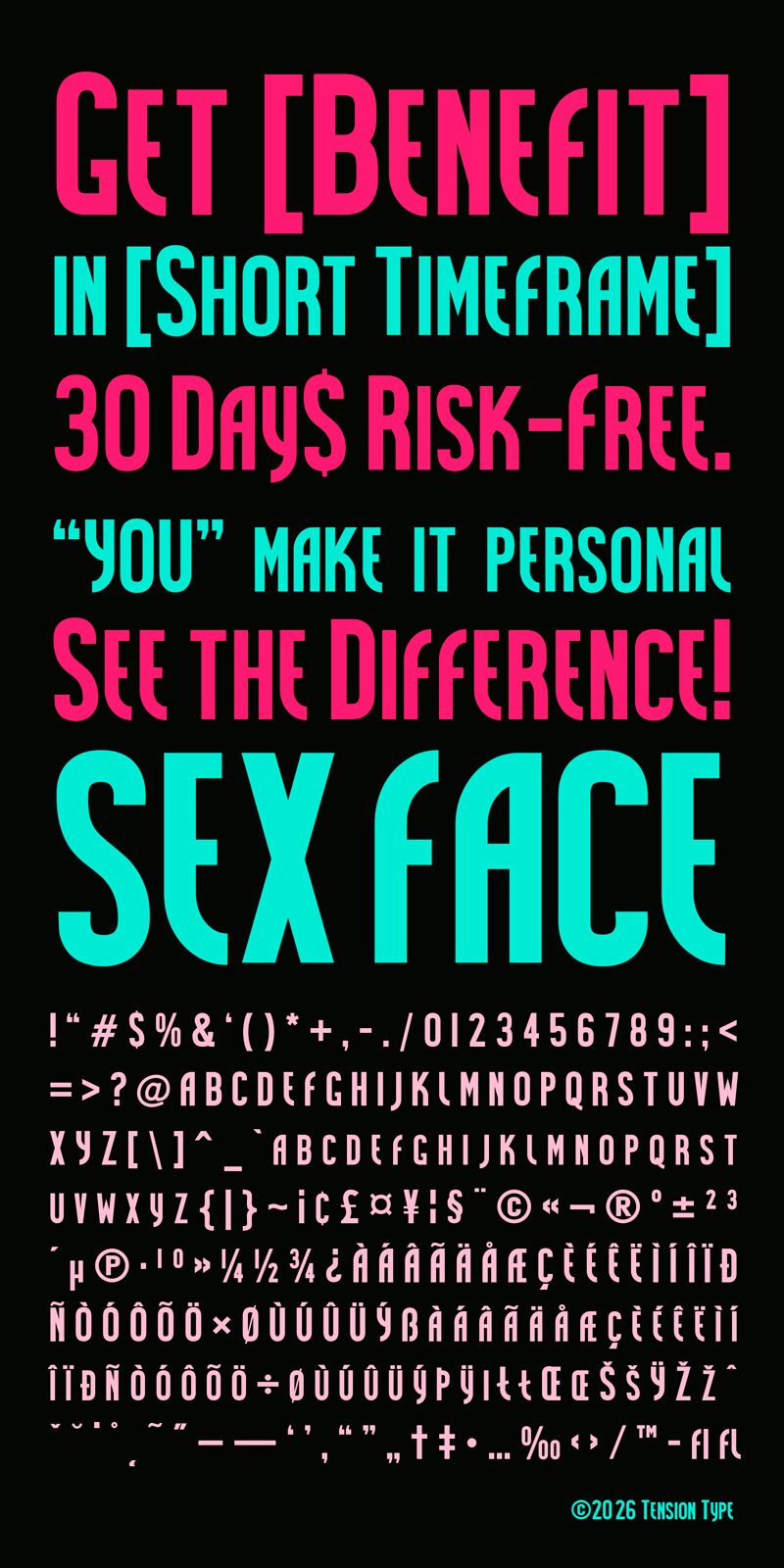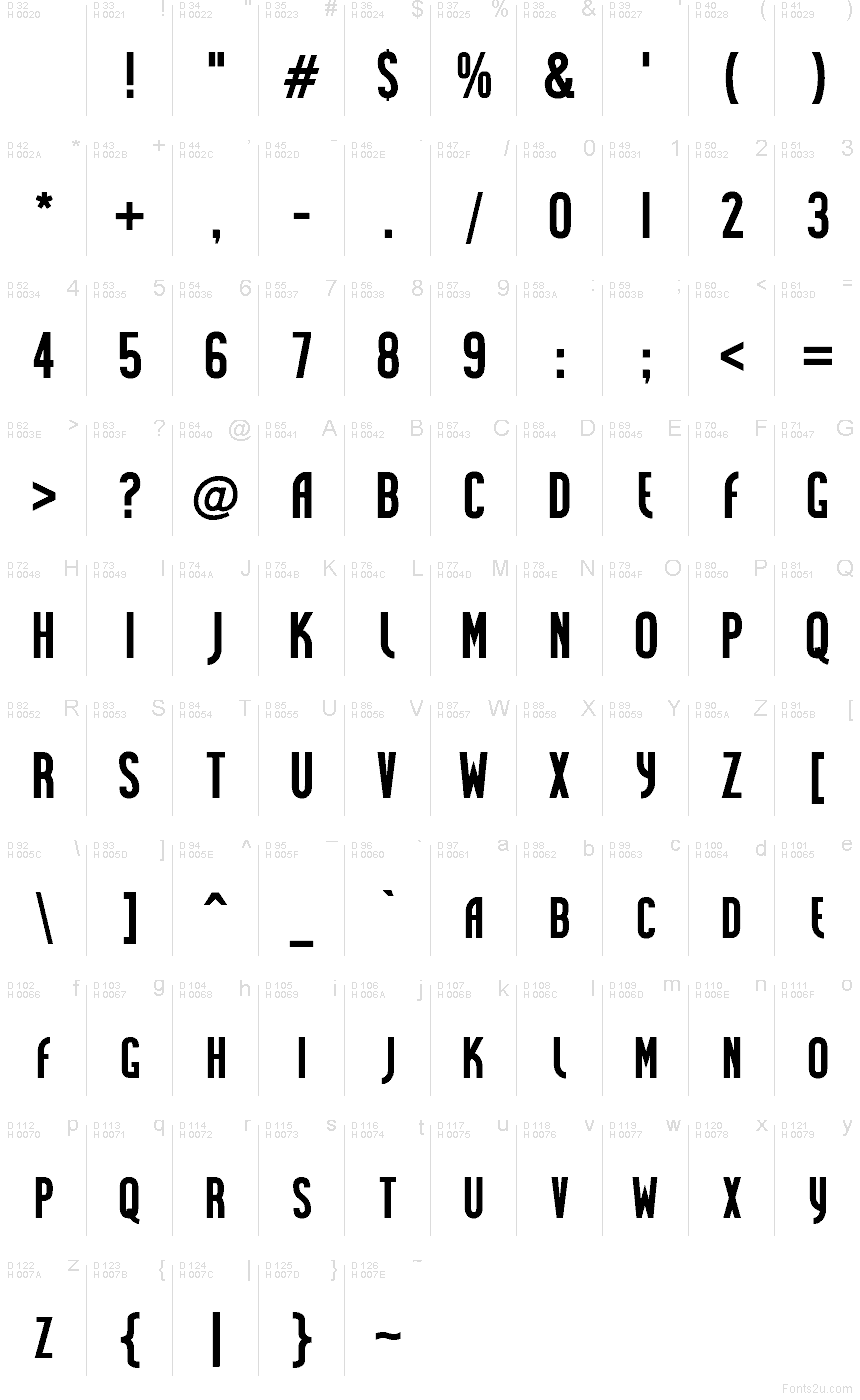
Sex Face Small Caps
Sex Face Small Caps est une police d’affichage rétro gratuite, caractérisée par des formes de lettres hautes et étroites ainsi que des découpes carrées qui lui confèrent un rythme rigide, typique des affiches. Le traitement en petites capitales assure une cohérence visuelle, tandis que les côtés plats et les courbes intérieures arrondies créent un profil graphique distinctif, inspiré des années 70.
Sex Face Small Caps fonctionne parfaitement pour les affiches, les pochettes d’albums, le branding, les titres éditoriaux et le packaging, là où un logotype compact et plein de caractère est nécessaire. Cette police gratuite possède suffisamment de structure et de détails atypiques pour convenir à la création de logos, à la signalétique et aux titres courts qui ont besoin d’une touche rétro sans pour autant être ornés.
Il s'agit de ma deuxième création de police sans empattement. J'adore les typographies condensées, c'est donc ce que j'ai réalisé. Idéal pour les titres, les affiches, les logos ou tout support grand format. Pas l'idéal pour du texte courant :)
Tension Type
Michael Tension
My second design of a sans serif font. I like condensed type a lot, so that’s what I did. A big learning curve!